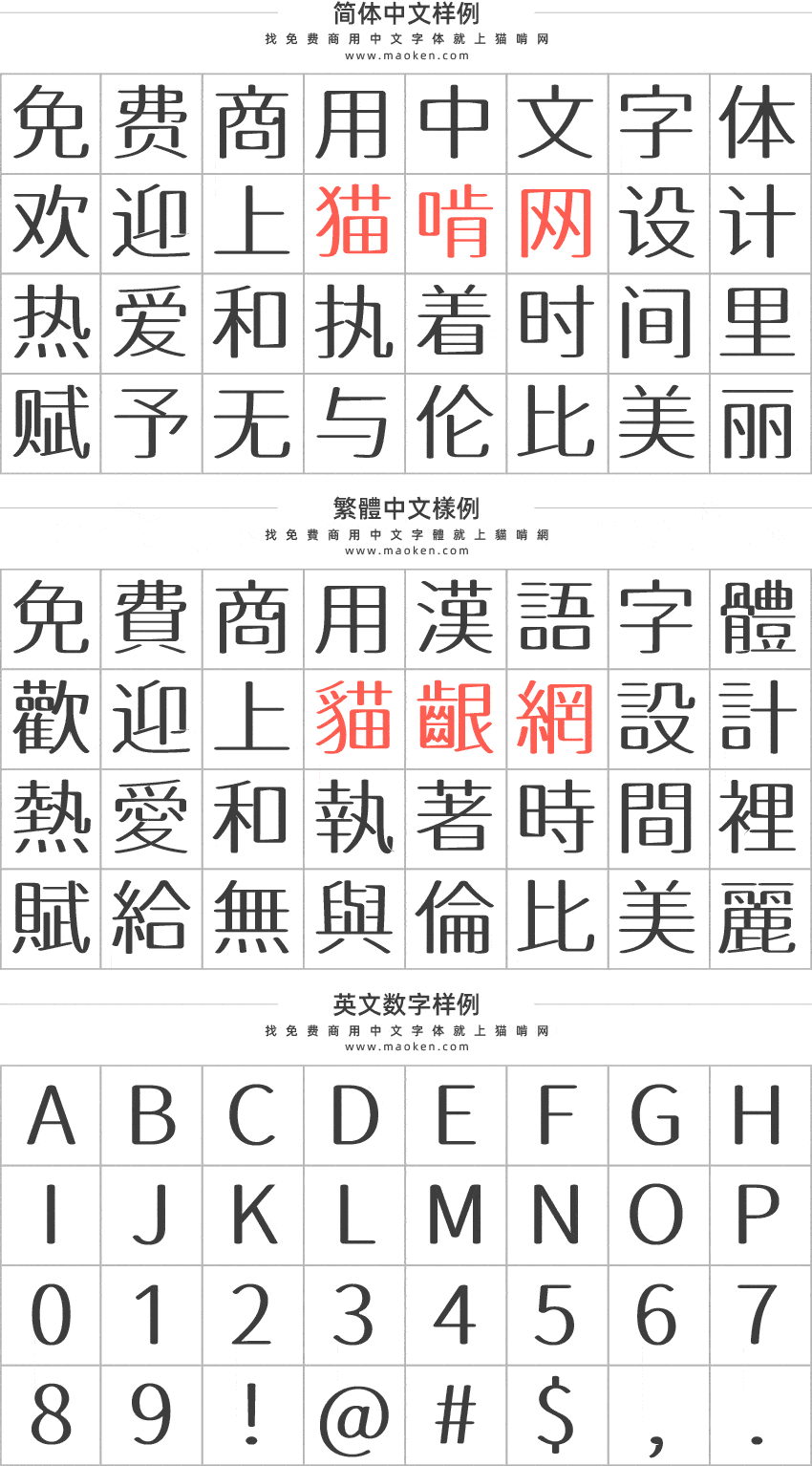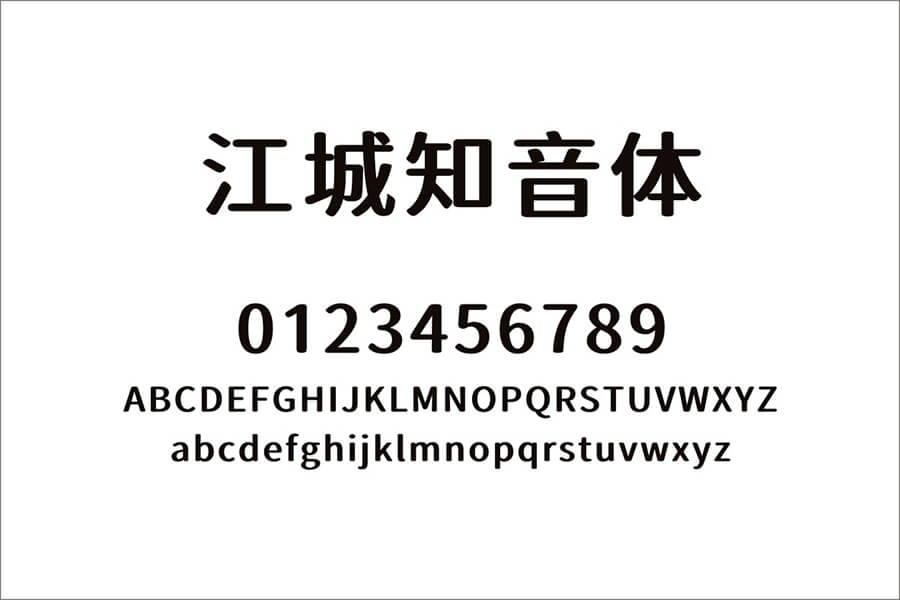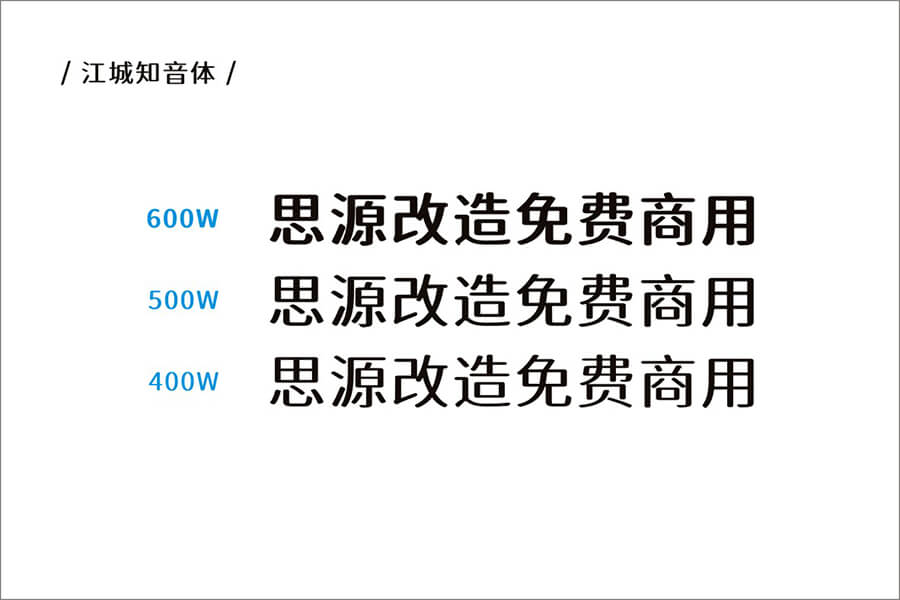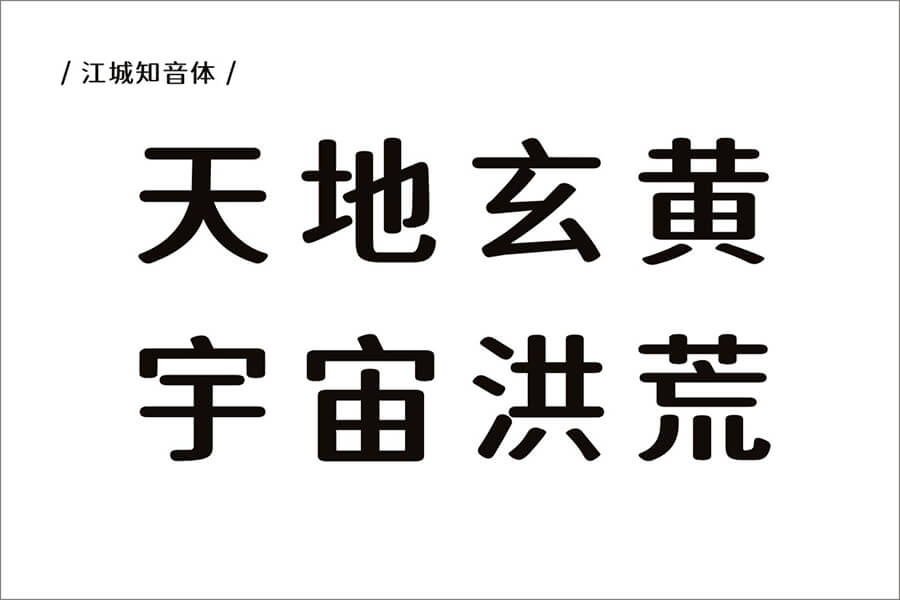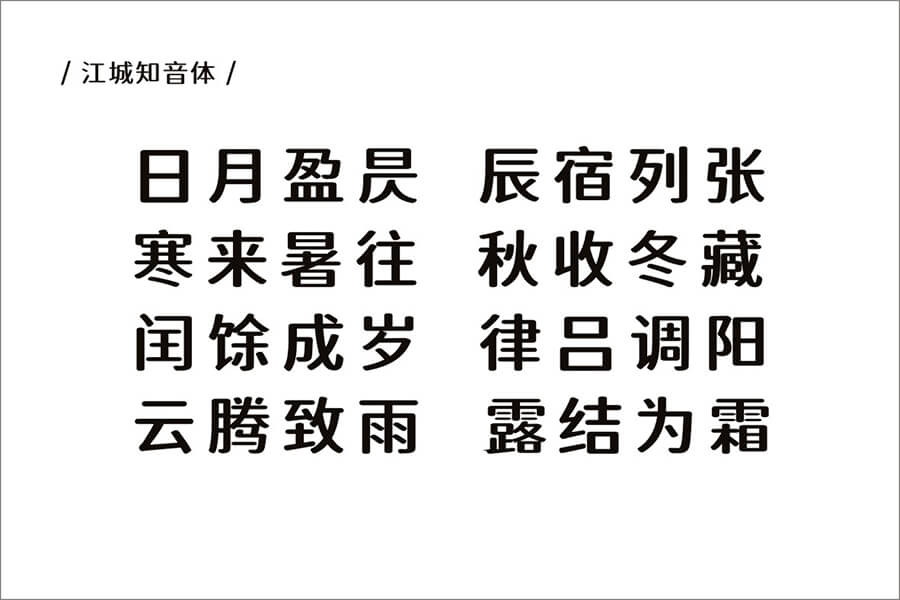
江城知音体:基于江城圆体改造更时尚的免费商用圆体字形
字体作者:刘鹏 (中国大陆) 字体字重:3个
江城知音体是基于江城圆体改造,把江城圆体横向减细处理,纵向增粗处理,得到的字体。这款字体是大神刘鹏的又一款基于思源字体进行改造的力作。刘鹏大神已经在猫啃网上发布了江城斜黑体、江城斜宋体、江城正义体、江城圆体等多款免费商用字体供广大设计师使用,猫啃君在这里再次对刘鹏大神表示感谢!
江城知音体跟思源黑体一样拥有超大的字符集,所以无论是简体还是繁体都基本上不缺字。并且江城知音体还拥有3个字重,能满足绝大部分的设计需求。
Ver 2.0(2021/03/24)
• 江城知音体更新了V2.0
• 修改网友反馈字形问题
• 重新优化了字形改造方式,减少大量毛刺、字宽、字距问题
• 西文字母及数字选用Baloo2改造
Ver 1.5(2020/09/05)
• 江城知音体更新1.5版本
Ver 1.0(2020/06/14)
• 江城知音体正式发布
在400w字重下“多”字明显小了,还有在几种字重下:“锦、记”两个字底部有多出来一些小角,“异”这个字也是错误的结构,大神改进下
此字体我刚使用过,发现在CJK范围内的“巽”字无法显示出来。难道没有制作?
所有字重的“给”字都有错误
说错了,瘦字在600w有错
瘦字在500w有错
逝字有问题
非常喜歡這個字體,但用在手機上字體太寬了 導致字體顯示不出來 (也就是所謂的字體斷頭斷腳)這點能否改進一下
非常喜欢这款字体,能否再增加个700W和900W的字体?
• 再粗的话,有些笔划多的字效果不好
不過齦字在500W有錯誤
字形、笔画不是大陆通用的,会被当作错别字。无法用于正式出版物。
• 建议用于海报标题等地方哦,刊物正文不建议使用
• 未来可能会慢慢完善,但缺少人工效对,难免有遗漏
江城系列字体可以代替好几套漫画嵌字所用到的字体了!!